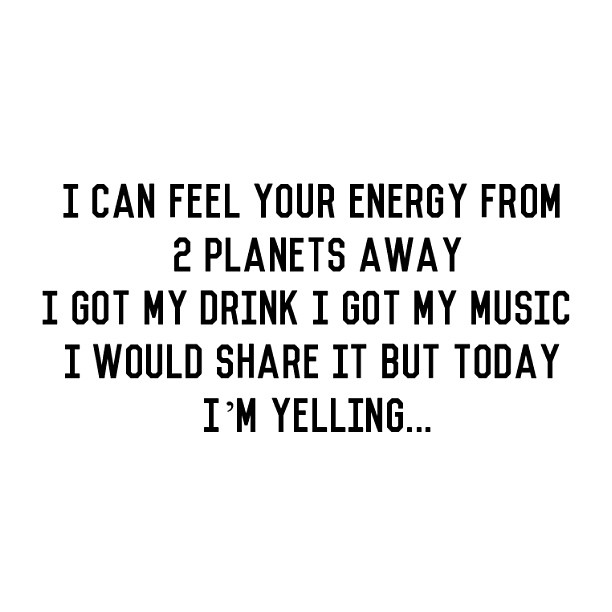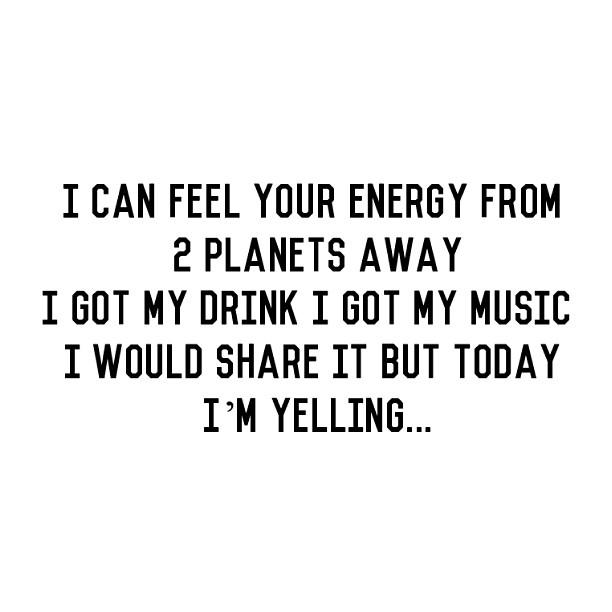
Wie lautet Schriftart wie auf dem Bild
wenn’s dir nur um die anmutung geht, dann was machine-artiges:
ist natürlich viel zu fett, hat aber immerhin auch diese glatt abgebissenen ecken, die als rückennummern auf sport-trikots so beliebt sind.
Ich tippe auf einen Freefont – der nicht passende Apostroph ist mE ein Zeichen dafür. Schau mal bei dafont und Konsorten.